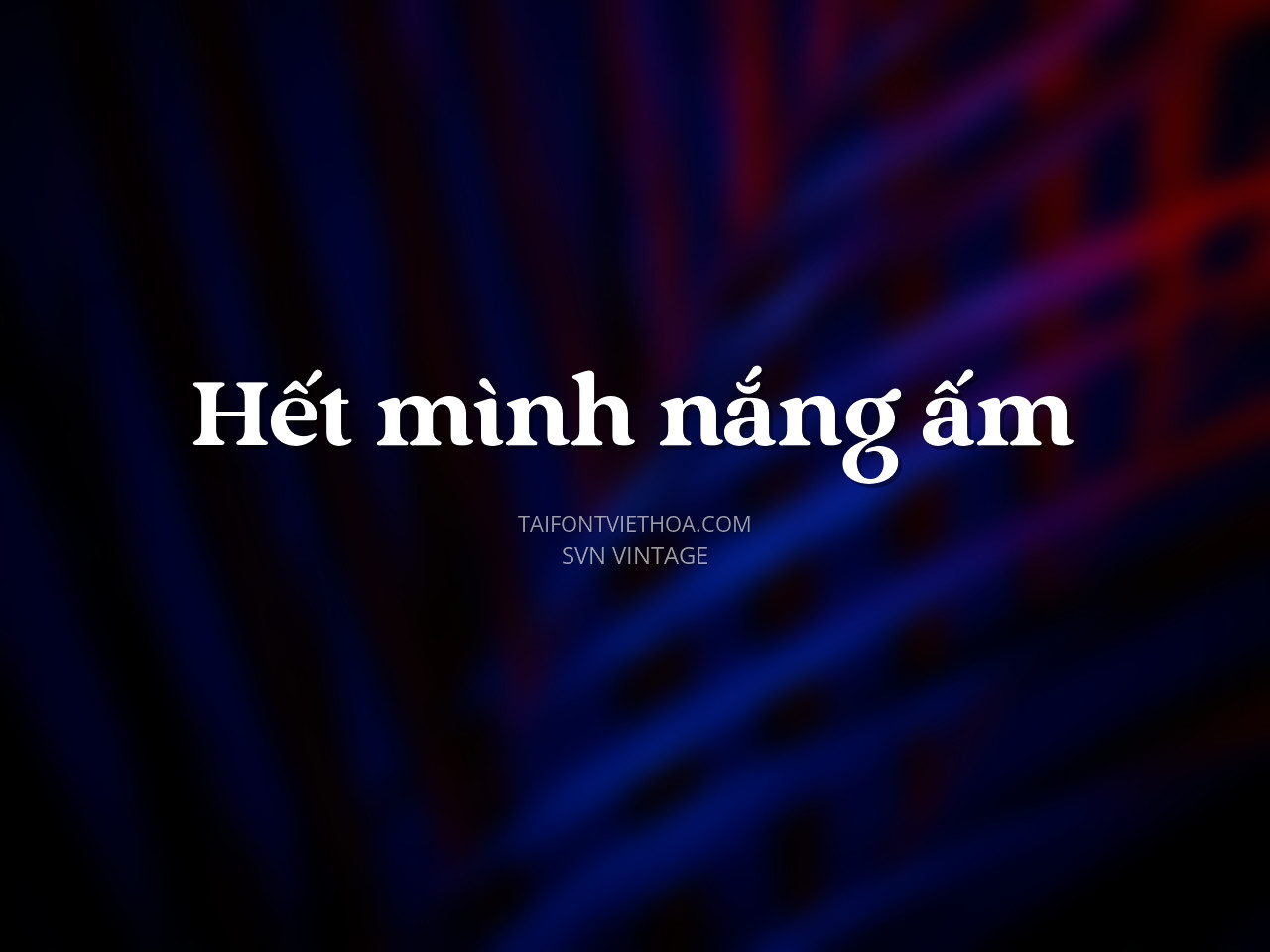
Font việt hóa SVN Vintage
Giới thiệu về Vintage – Font serif cổ điển phong cách retro
Vintage (tên gốc: Vintage Typeface) là phông chữ serif cổ điển được thiết kế bởi Vunira Design(Indonesia) và phát hành rộng rãi trên Creative Market từ năm 2018. Font này lấy cảm hứng từ các biển hiệu, poster và typography đầu thế kỷ 20, mang đến cảm giác sang trọng, đậm chất retro cho bất kỳ thiết kế nào. Bản quốc tế của Vintage hỗ trợ trên 60 ngôn ngữLatin mở rộng, phù hợp với nhiều dự án toàn cầu và đảm bảo khả năng hiển thị tốt trên hầu hết các phần mềm thiết kế đồ họa hiện nay.
Phiên bản SVN Vintageđã được STYLEno.1 FontsViệt hóa trọn bộ, bổ sung dấu tiếng Việt chuẩn, căn chỉnh lại kerning và tối ưu hiển thị cho cả in ấn lẫn digital. Đội ngũ taifontviethoa.comđã trực tiếp chọn lọc, kiểm thử kỹ lưỡng trên các nền tảng như Adobe Illustrator, Photoshop, Canva, CorelDRAW…, đảm bảo font chạy mượt, không lỗi dấu, không vỡ nét. Nhờ vậy, Vintage Việt hóa sẵn sàng đáp ứng mọi nhu cầu sáng tạo – từ thiết kế poster, branding, ấn phẩm sự kiện cho tới thiệp cưới, bao bì sản phẩm phong cách cổ điển.
Đặc điểm thiết kế, ứng dụng và ngành nghề phù hợp
Vintage thuộc nhóm serif cổ điểnvới cấu trúc chữ dày dặn, nét chân thanh mảnh đặc trưng, tỷ lệ chữ cân đối và các chi tiết bo tròn nhẹ giúp tạo cảm giác mềm mại nhưng vẫn sang trọng. Font này nổi bật với phần đầu và chân chữ sắc nét, kết hợp cùng các glyph đặc biệt như số, ký tự trang trí giúp tối ưu khi làm tiêu đề lớn, logo hoặc các ấn phẩm nghệ thuật mang hơi hướng retro.
Ứng dụng tiêu biểu
– Logo & nhận diện:Lý tưởng cho thương hiệu café cổ điển, studio ảnh vintage, shop thời trang retro.
– Poster & sự kiện:Thiết kế poster quảng cáo, banner triển lãm, poster nhạc cổ điển, ấn phẩm nghệ thuật.
– Thiệp & bao bì:Thiệp cưới, nhãn mác sản phẩm thủ công, hộp quà tặng sang trọng.
Ngành nghề phù hợp
Vintage là lựa chọn lý tưởng cho các ngành sáng tạo như quảng cáo, tổ chức sự kiện, thiết kế thương hiệu, studio nghệ thuật, shop thời trang, nhà hàng, quán café… Khi phối hợp với các font sans-serif hoặc script hiện đại, Vintage giúp tổng thể thiết kế trở nên hài hòa, cuốn hút và nổi bật tinh thần retro cổ điển. Tải ngay phiên bản Việt hóa tại taifontviethoa.com để trải nghiệm trọn bộ glyph và ứng dụng vào dự án của bạn.